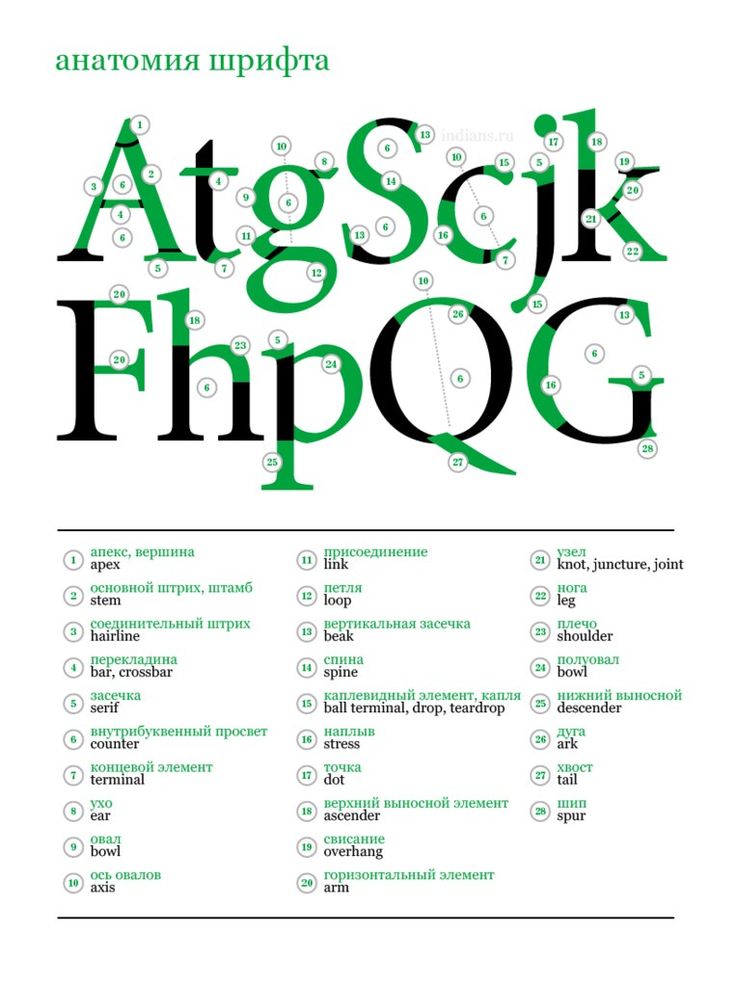
Разборчивость и удобочитаемость как характеристики шрифта
Подбирая типографское оформление для веб-ресурсов, приходится учитывать массу нюансов, чтобы в готовом виде страница получилась удобочитаемой, а пути доступа к её содержимому были просты и понятны. В общем, сводится всё к двум аспектам подачи текста пользователю: разборчивости и удобочитаемости. Разборчивостью принято называть различимость слов и текстовых блоков, обусловленную способом их размещения на странице. А удобочитаемостью — распознаваемость каждого отдельного символа, обусловленную их строением, начертанием шрифта. Рассмотрим эти свойства подробнее, познакомимся со специальными приёмами улучшения типографского оформления проектов, собственно, об этом наша статья.
Удобочитаемость
Давайте начнём с удобочитаемости. Важно понять, за счёт чего один шрифт читается удобнее, легче другого. Гарнитуру шрифта нужно выбирать, исходя из её дальнейшего предназначения. Задайте себе всего несколько главных вопросов: Много ли у вас самого текста? Это основной текст или заголовок? Он решает чисто рабочие задачи или скорее служит украшением? Будет ли он использоваться в паре с другим шрифтом? Отражает ли начертание шрифта тематику материала?
Кроме того, важно помнить, что у шрифтов различного начертания и назначение разное.
Например, Garamond был изначально разработан для оптимальной читаемости текстов большого объёма. Есть мнение, что это был ещё и самый экологичный шрифт своего времени, снижавший расход типографской краски. Шрифт Bell Centennial был введён в обращение корпорацией AT&T в 1970-е годы и предназначался для издания телефонных справочников. Они печатались на дешёвой бумаге, поэтому Bell Centennial был разработан с учётом необходимости направленного распределения краски в ходе печати. А в эпоху цифровых технологий появились шрифты, разработанные специально для отображения текстов на дисплее, такие как Georgia и Verdana. Azura — довольно молодой шрифт, чья «специализация» — тексты, читаемые непосредственно с экрана.
Короче говоря, лучше знать сферу применения шрифта, который вы намерены использовать. Есть весьма универсальные шрифты, пригодные для набора ими текстов различного характера, доступные в виде нескольких модификаций разной толщины штриха. Область применения других довольно ограничена, у них, так сказать, особое назначение.
Итак, мы подошли к первому из нескольких параметров удобочитаемости гарнитуры:
Декоративный шрифт в противоположность текстовому
Некоторые шрифтовые гарнитуры были изначально разработаны для набора ими крупных надписей, тех же заголовков. Обычно они хуже читаются в мелких масштабах, и их не стоит применять для массивов основного текста. Они и называются декоративными. Ниже приведён пример декоративного шрифта Knockout, одного из моих любимцев.
Другие же гарнитуры специально предназначены для набора больших объёмов более мелкого основного текста. Они называются текстовыми шрифтами или шрифтами для набора текстовых массивов.
Есть ещё множество промежуточных вариантов. Я обычно нахожу шрифт, подходящий для решения моей задачи, учитывая при этом, что мне придётся подбирать к нему и парный шрифт, а дальше иду практическим путём. Я заранее отсеиваю все непригодные для моего текущего проекта варианты, но новичкам порой не избежать трудностей на данном этапе проб и ошибок.
Шрифт с засечками в противоположность шрифту без засечек
Какие же из них удобнее для чтения: шрифты с засечками или без? История свидетельствует, что шрифты с засечками всегда считались более удобочитаемыми, поскольку именно им всегда отдавали предпочтение для набора в типографиях больших массивов текста. Нашим глазам легче скользить по тексту, отпечатанному шрифтом с засечками, они меньше устают при чтении, скорость которого при этом повышается.
Однако, есть и много вполне разборчивых шрифтов без засечек. Кажется, что онлайн шрифты без засечек используются для набора основного текста чаще, чем когда-либо прежде. По-моему, причин тому несколько. Символы с более простым контуром, вроде бы, лучше вписываются в принятый ныне дизайн и смотрятся современнее. К тому же, нам, как правило, не приходится читать на веб-сайтах помногу, и шрифты без засечек отлично справляются с отображением компактных текстовых фрагментов.
Нужно заметить, что вопрос этот остаётся спорным – есть мнение, будто шрифты с засечками плохо масштабируются на экране в сторону уменьшения их калибра, вследствие чего существенно снижается их удобочитаемость.
Другие же люди считают, что никакой разницы нет. Я же придерживаюсь следующей линии: в данной конкретной ситуации это решение годится? Мне самому удобно читать текст, оформленный мной таким образом?
Икс-высота
Ещё одна учитываемая характеристика шрифта — икс-высота его символов. Её обычно берут в расчёт при выборе шрифтов для основного текста. Икс-высота это, ну, вертикальное расстояние от низа до верха строчной буквы «x» данной гарнитуры. Величина верхних и нижних выносных элементов символов значения не имеет. Вас может удивить разница значений икс-высоты между шрифтами различного начертания. Мелкие калибры более крупных по икс-высоте шрифтов, как правило, разборчивее при чтении.
Разборчивость
Разборчивость шрифта оценивается по степени податливости набранного им текста для зрительного восприятия читателем, по тому, насколько легко ему распознавать и усваивать контент на уровне отдельных слов и их групп. Разборчивое оформление текста — своего рода искусство, мастерство, нарабатываемое со временем, по мере накопления в арсенале дизайнера удачных комбинационных решений.
Риторически уместное использование Баухауза 93
Соответствие индивидуальности шрифта тону произведения иногда субъективно и, конечно, не является точной наукой. Хороший способ убедиться, что вы выбираете подходящие шрифты, — это использовать шрифт, который кажется полностью противоположным тому, что вы пытаетесь передать. Увидев, как «неправильно» это может выглядеть, вы сможете выбрать более подходящий шрифт. Ниже есть две колонки слов. Столбец А пытается задать соответствующее настроение чувству, которое вызывает это слово.